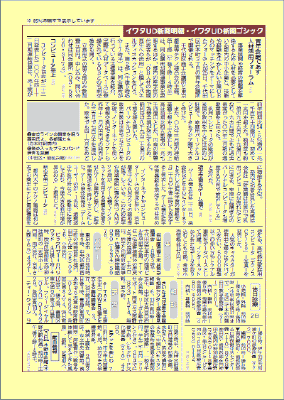
イワタUD新聞明朝の有効事例
ユニバーサルデザインの視点に基づき、新たに開発された新聞書体です。「イワタUD新聞明朝体」は、見やすく読みやすい新聞紙面を構成できる次世代の新聞書体として設計されました。
UD新聞明朝使用例
開発の背景(新聞文字を取り巻く環境)
新聞紙面は戦後間もない1951年(昭和26年)に1ページ15段,1段15文字制がスタートしました。その後時代とともに大きな文字が必要とされましたが、新聞は従来の枠の中で1段の文字数を減らすことにより対応してきました。
そして高齢化社会が進むにつれ、新聞紙面の大文字化のニーズが急速に進み、2008年、多くの新聞社において、紙面の組み体裁を変更したり、1ページ15段の枠から脱却して12段にして文字を大きくする社も登場しました。しかし、本文文字は単純にサイズを拡大するだけでなく、その大きさに合うよう、文字の品質(デザイン)そのものを見直す必要にも迫られていました。このような環境の中で、イワタとしては次の点を基本理念として「大文字」にふさわしい新聞本文文字を開発するに至りました。
UD 新聞明朝の基本コンセプト
・ユニバーサルデザインの思想に基づき、誰もが見やすく、読みやすい文字である こと
・文字の品位が維持されると同時に、美しい紙面が構成できる統一された書体であること
・デザインコンセプト
▶線率(縦横線の比率)を見直した目にやさしい文字縦横線の線幅を近づけることにより、従来の明朝体にみられる横線の細さ、文字のちらつき感を無くす。
▶文字の正方化に対応
標準使用扁平率を85%とし、文字正方化の流れに対応。
従来より自然な文字組みの体裁が実現可能。
▶可読性と品位を考慮した漢字と仮名のバランス
従来、仮名を限界まで拡大して文字を大きく見せるケースが多かったが、漢字と仮名の大きさと太さのバランスを見直し、読みやすさと品位を考慮。
デザインの特徴(漢字)
1.横線が従来の明朝体より太い
→ 縦横比を極力抑え、遠近感をなくすことで、明朝体特有のちらつきを軽減
※ UD新聞明朝と従来新聞明朝との線幅比
[縦線] UD新聞明:イワタ新聞中明:イワタ新聞明 = 1.22:1.26:1
[横線] UD新聞明:イワタ新聞中明:イワタ新聞明 =1.78:1.27:1(80%扁平時)
2. エレメントが控えめ
→ ウロコ・ゲタなどの装飾を最小限の大きさにすることで、太さを感じさせず
画線をのびのび見せる
3. ハネ,打ち込み,起筆部のはみ出し等を省略
→ 小サイズで潰れる原因となる狭い空間を極力なくした
4.横線の密度によって、横線の太さを段階的に調整
→ 横線が太いため、画数の多い文字での潰れや濃度ムラを回避
5.デフォルメ(変形)しすぎず、本来の明朝体の字形に近づける
→ 文字や部首本来のバランスを追求。文字を正方化しても変形しにくい
(従来は文字が小さく扁平率が高かった為、文字の一部を大きくせざるを得なかった)
6.従来の新聞明朝で埋もれがちだった縦線の起筆部を出す
→ 小サイズでの黒みの偏りを軽減するとともに、字形の不自然さをなくす
※ その他、デザインの違いが顕著な例(上;UD新聞明朝,下;イワタ新聞明朝)
デザインの特徴(仮名)
1. 巻き込みを少なく
→ ふところを広げ、字形をはっきり見せる
2.濁点・半濁点を大きく
→ 小サイズでの識別を考慮